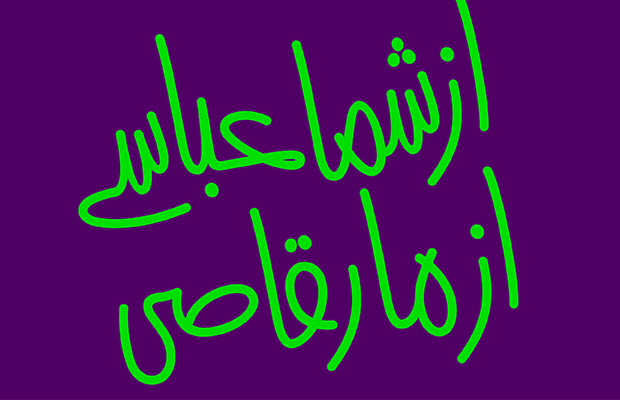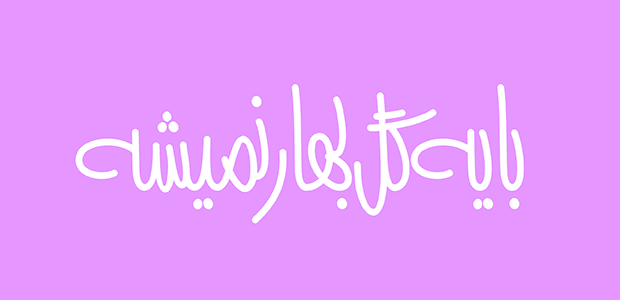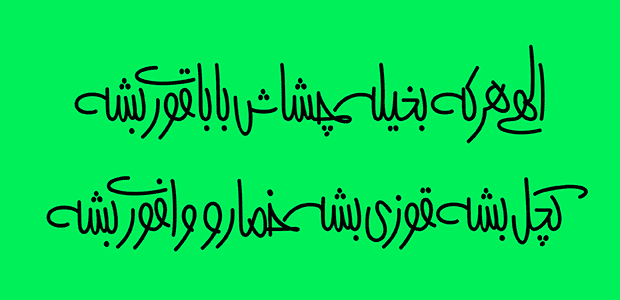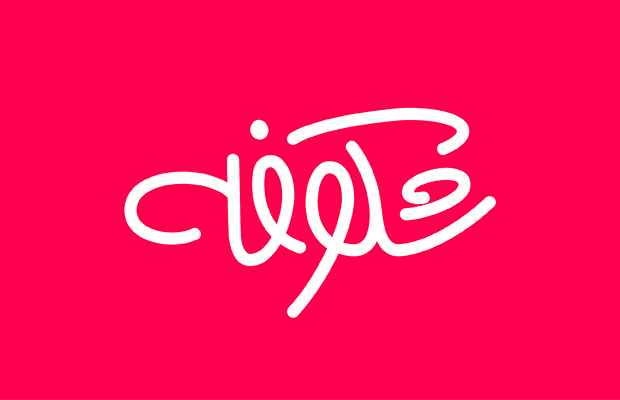
درباره قلم فرزاد
فونتها نیز مانند آدمها دارای کاراکتر و شخصیت هستند. واژۀ Character در انگلیسی که هم به معنای فونت و هم شخصیت بکار میرود، زیاد بیربط بنظر نمیرسد. شناخت این ویژگی برای هر طراح گرافیک از ضروریات است و با علم به این موضوع میتوان مناسبترین فونت را نسبت به موضوعی که برای آن طراحی میکنیم، انتخاب کرد. یکی از این دستهبندیها، فونتهای دستنویس (Hand Script) است. طراحی "فونت فرزاد" کوششی در این جهت است. فونتهای دست نویس حال و هوایی صمیمانه، خودمانی و ساده دارند و اگر درست انتخاب و بکار برده شوند، میتواند کارساز باشد. من طراحی فونت، خوشنویسی و نقاشیخط را حدوداً از ده سالگی شروع کردم، تا به امروز که همچنان علاقه به آن را حفظ کردهام. از طراحی حروف فارسی تا لاتین